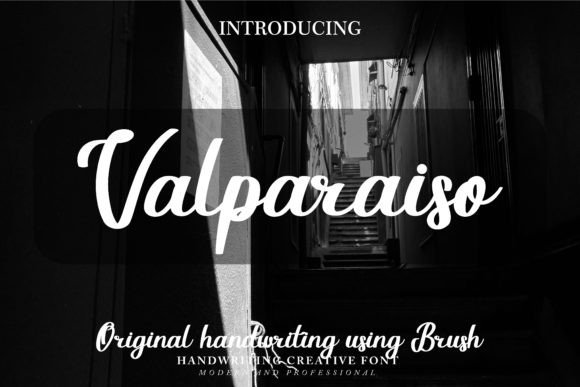
Valparaiso
Jika anda sedang mencari aset berkualiti tinggi seperti Valparaiso, pakej premium ini merupakan pilihan yang hebat untuk projek kreatif anda.
Dicipta dengan ketepatan, Valparaiso menyediakan vektor yang bersih, tipografi yang licin dan lesen komersial untuk ketenangan fikiran.
Sama ada anda mencipta produk POD (Print on Demand), jemputan perkahwinan atau grafik media sosial, Valparaiso amat bersesuaian.